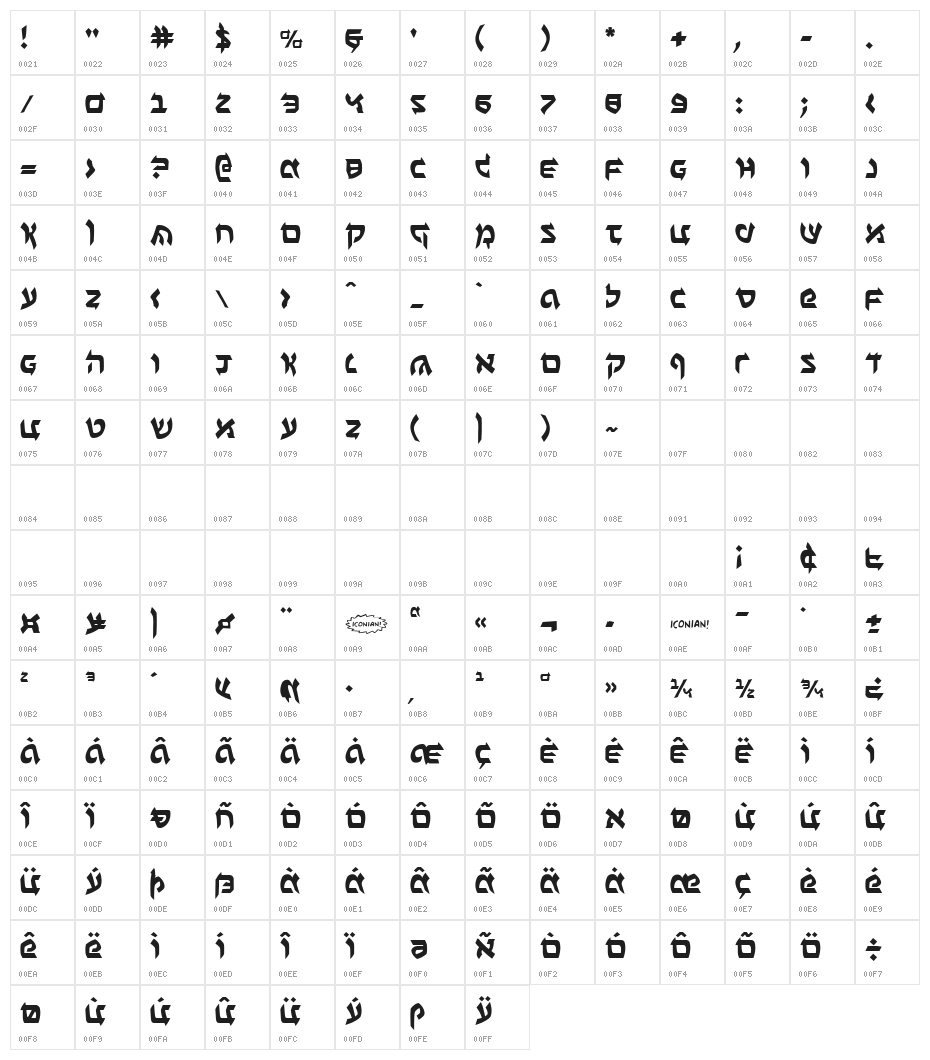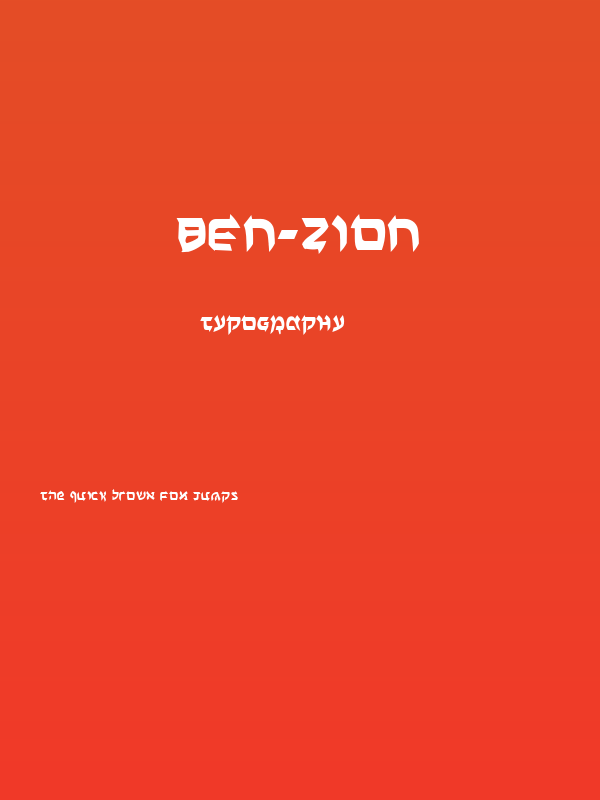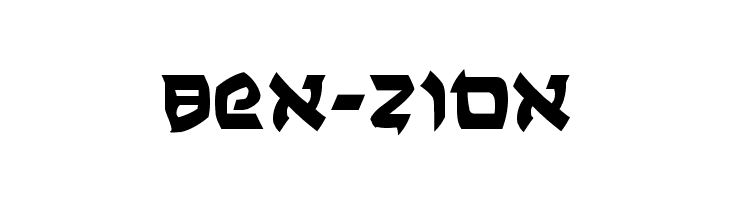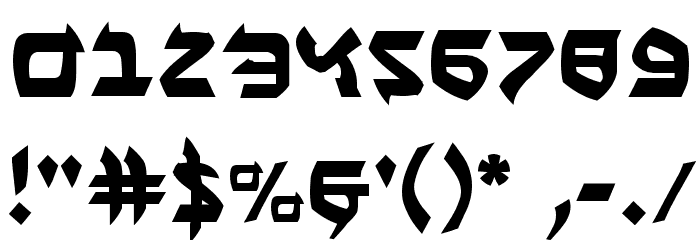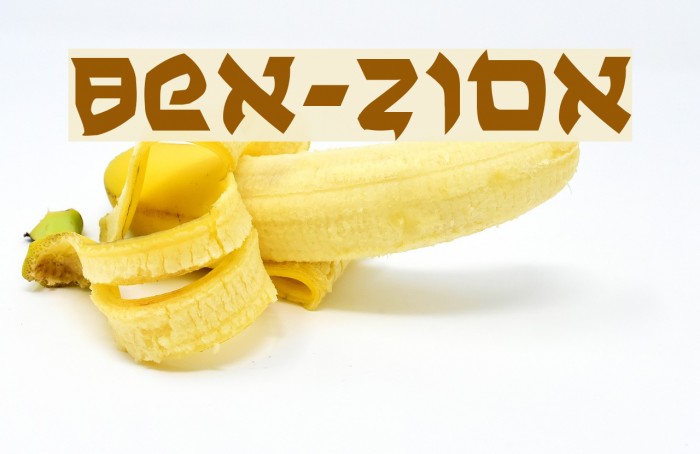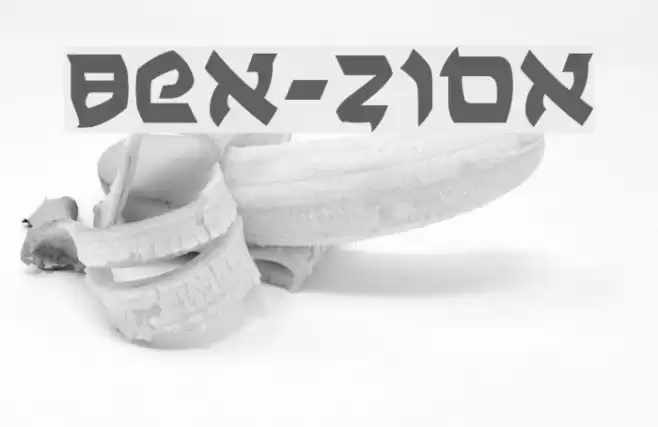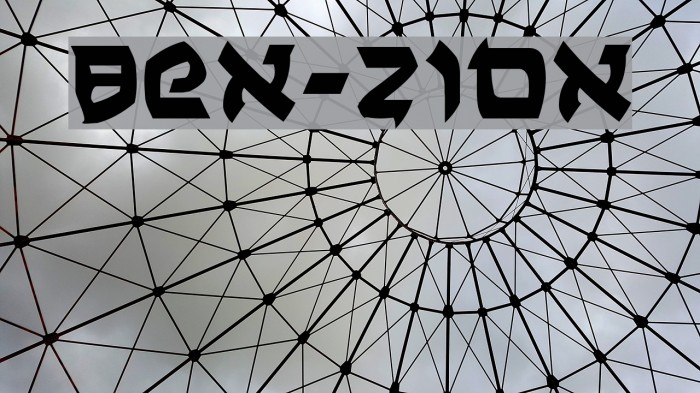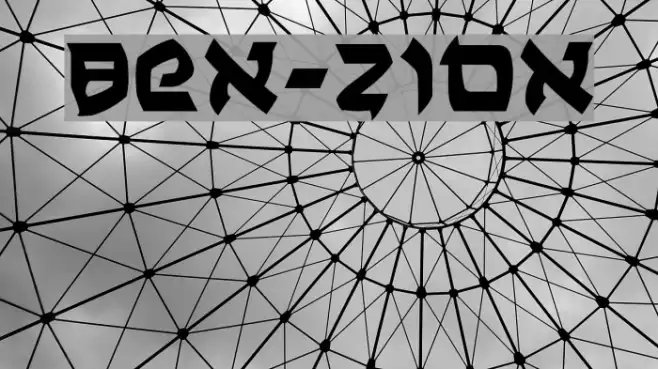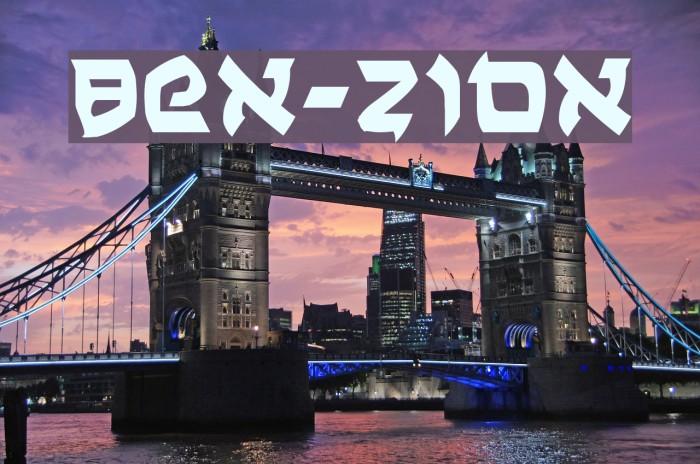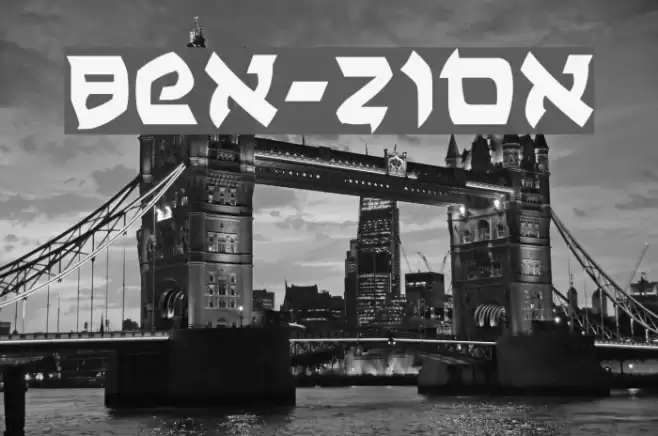
Ben-Zion Font
| Projets proposés | Ideal for sci-fi themed designs, video game graphics, posters, and branding that requires a modern and edgy look. |